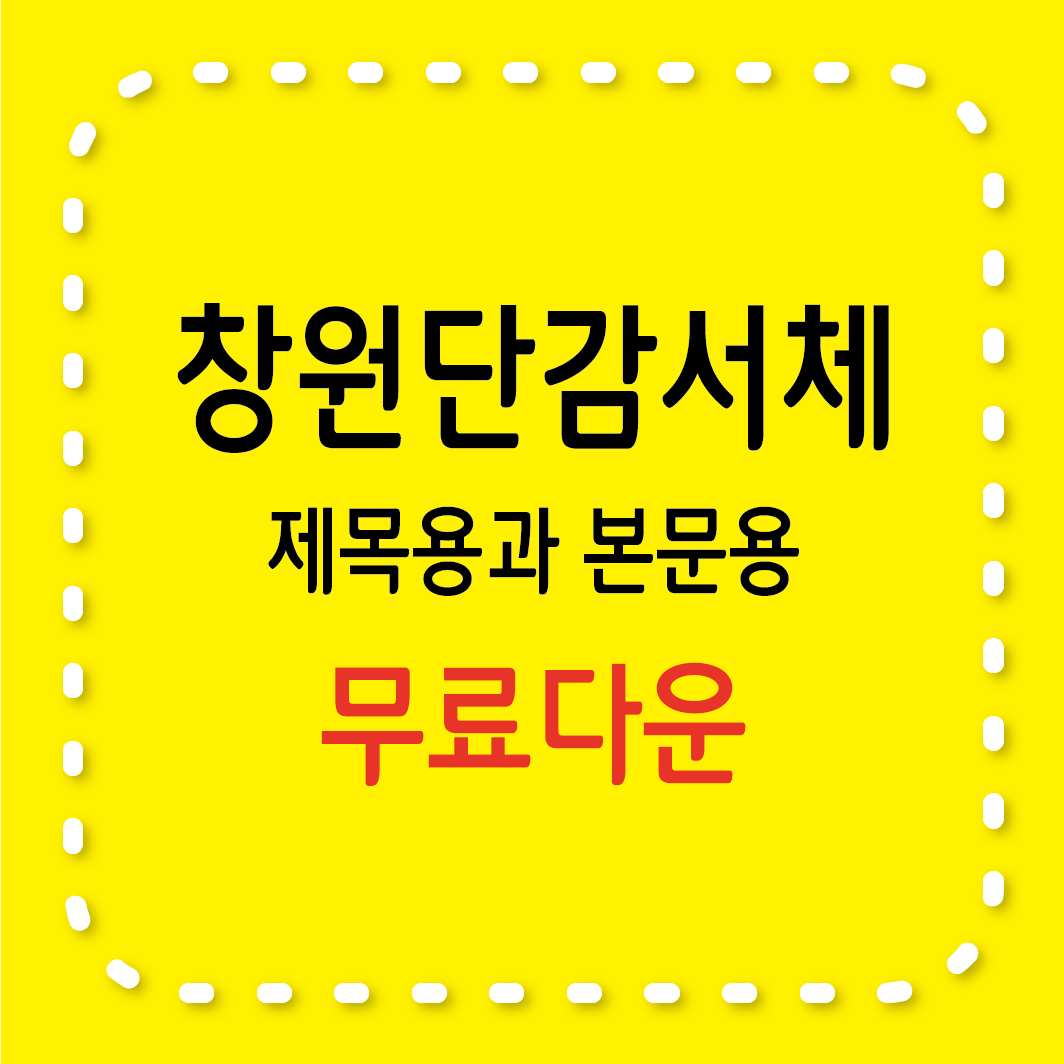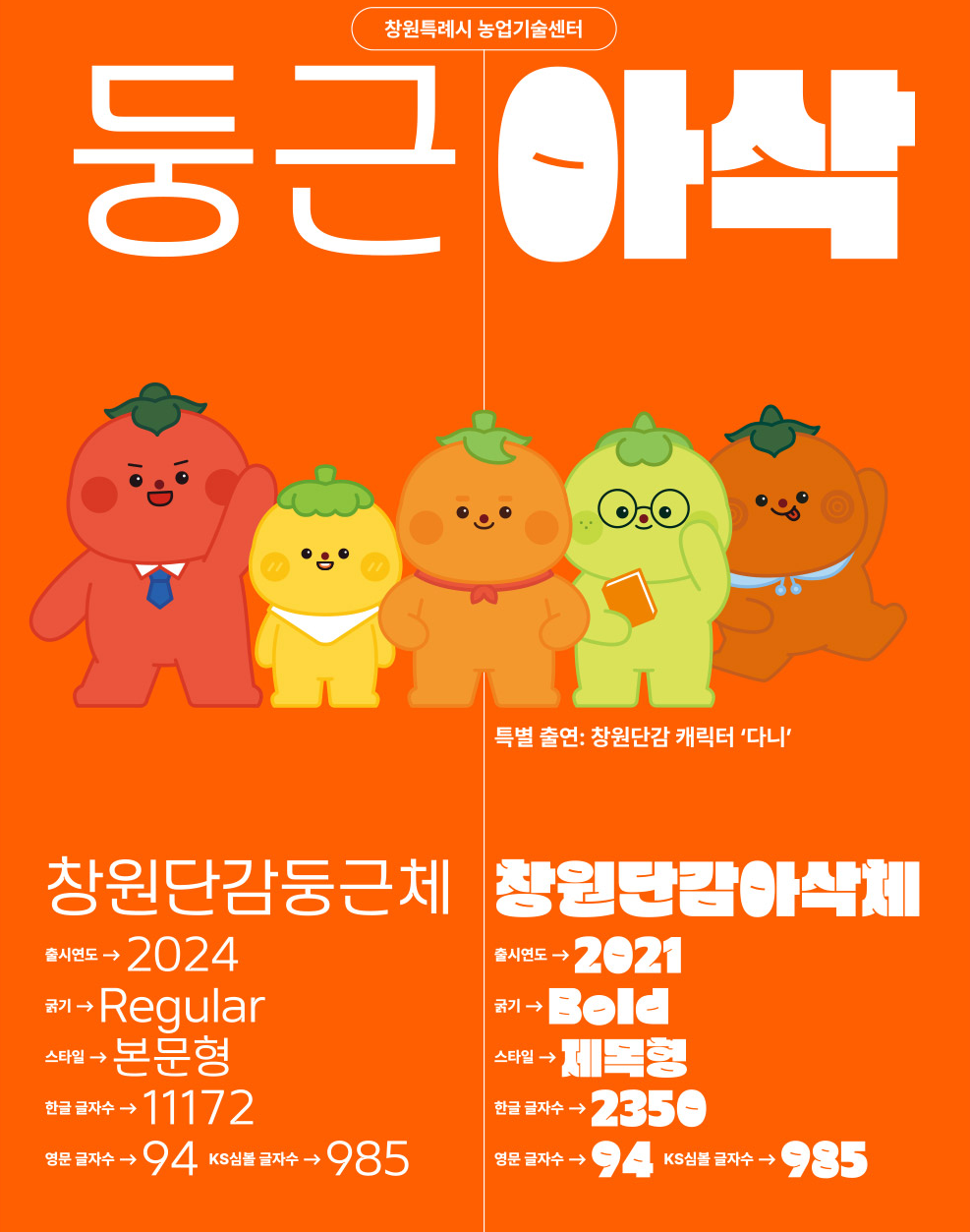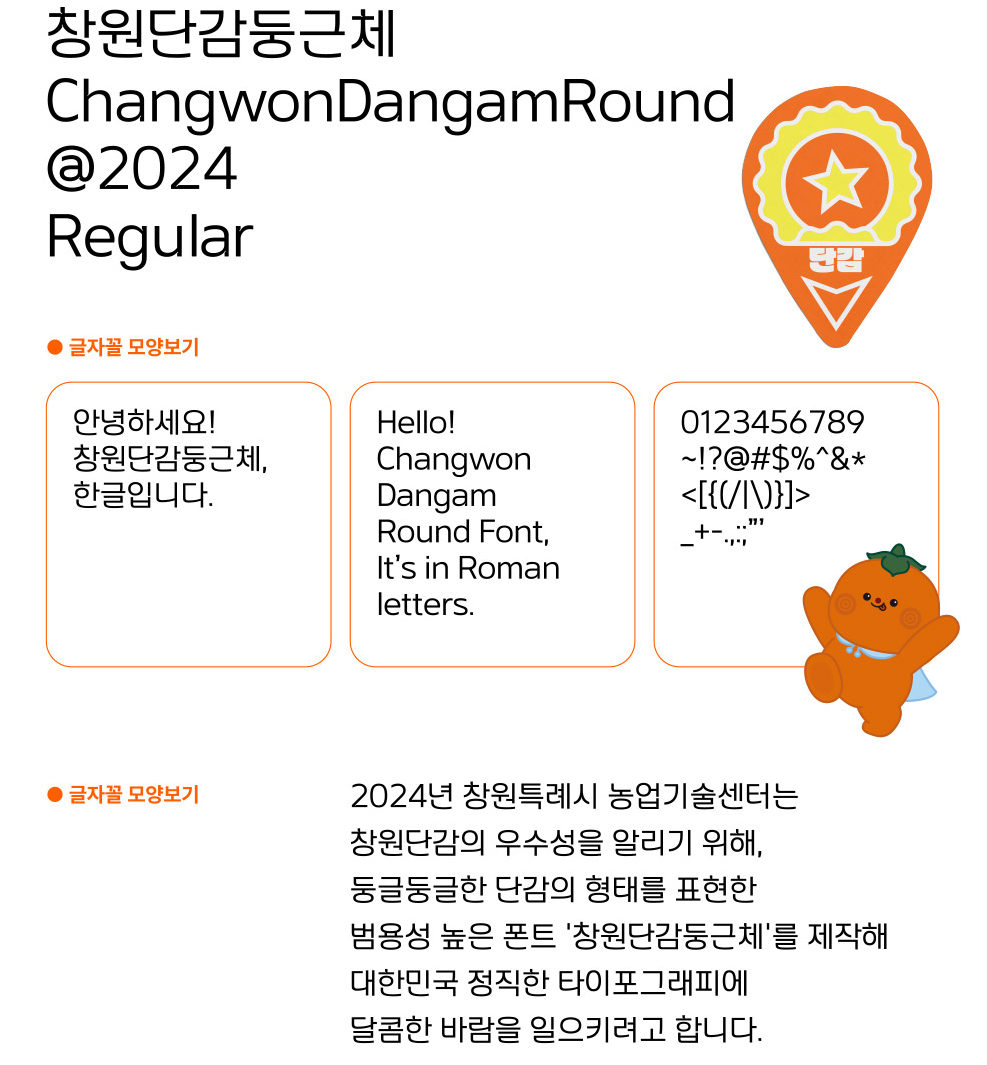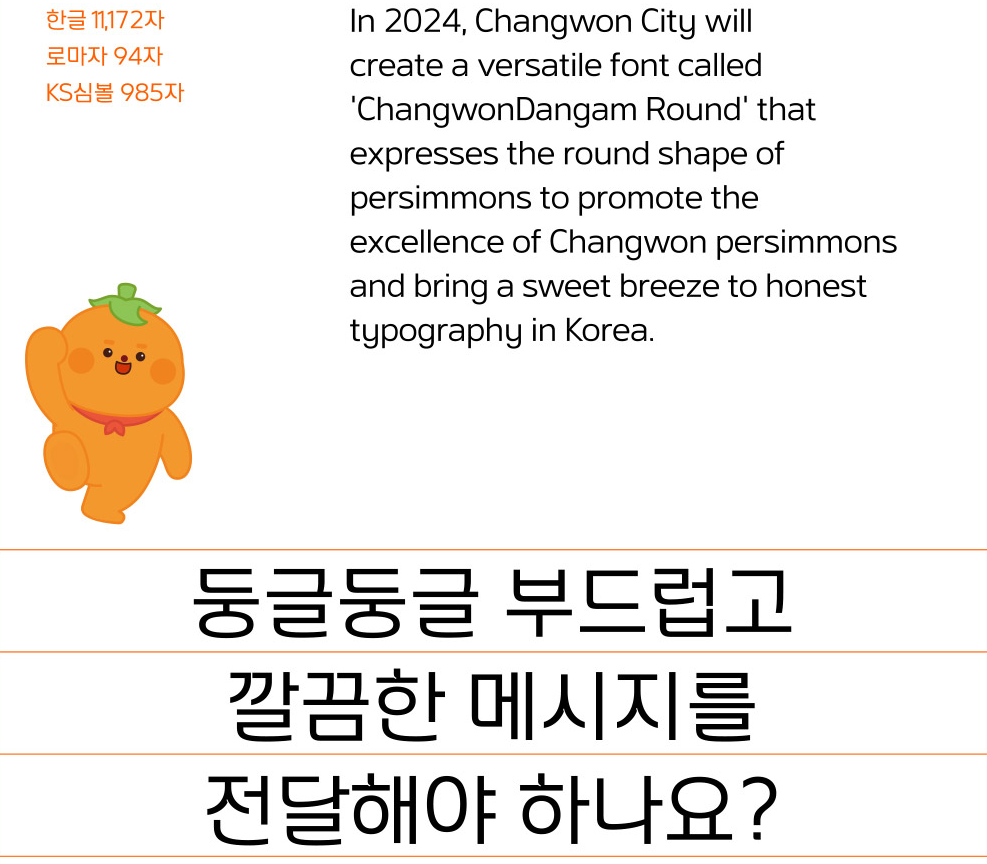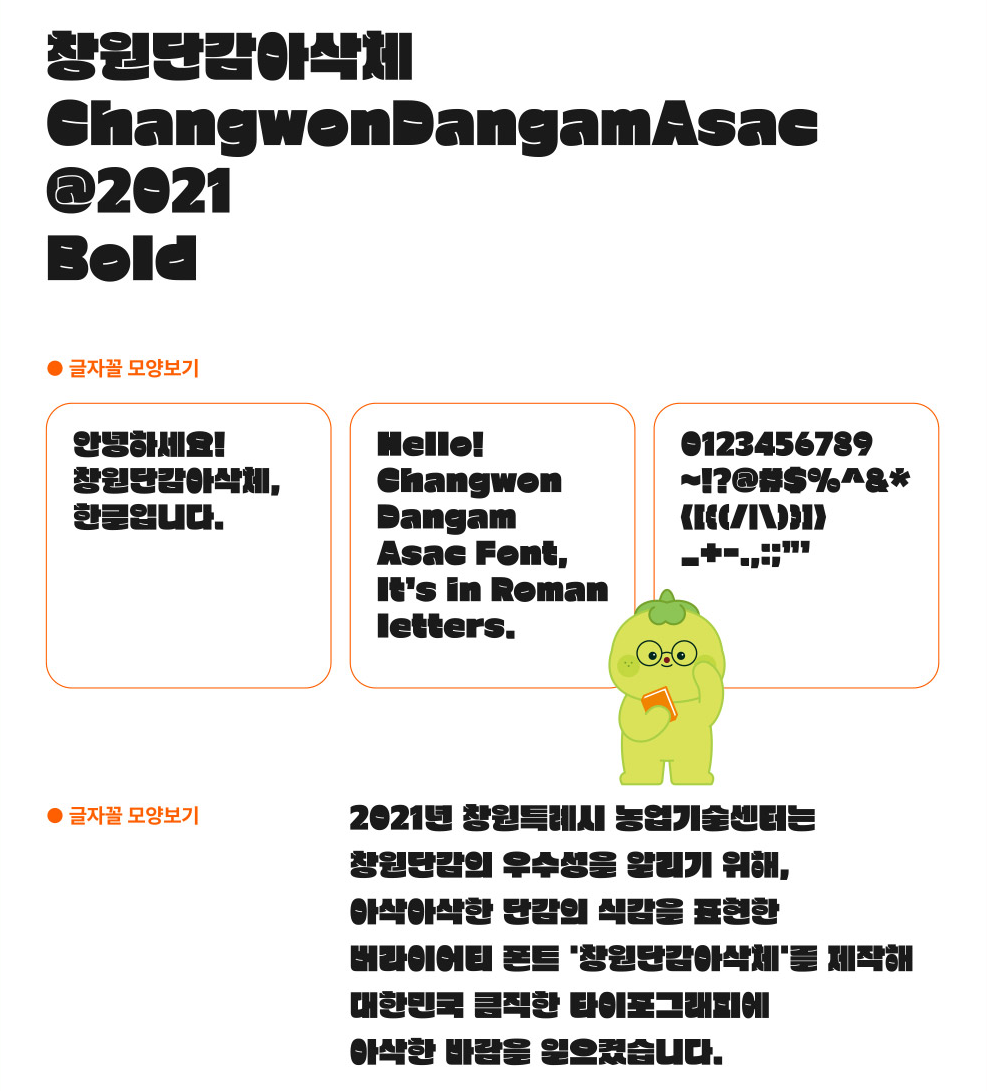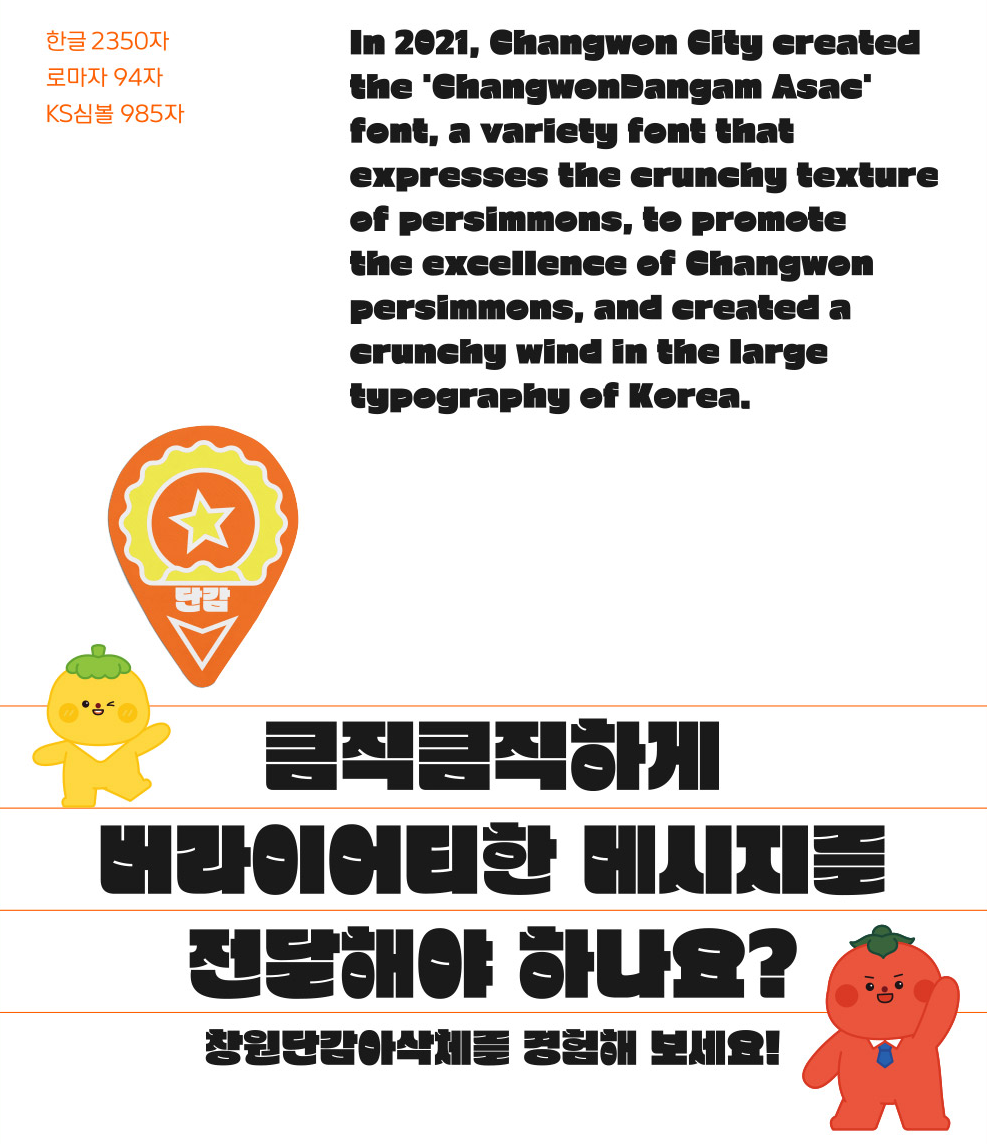
지방자치단체에서 배포하는 무료 폰트 중, 감성과 실용성을 모두 담은 서체를 찾고 계셨나요?
‘창원단감서체’는 제목용과 본문용을 모두 갖춘 감각적인 폰트로, 누구나 자유롭게 사용할 수 있습니다.
창원단감서체란?
‘창원단감서체’는 경상남도 창원시에서 공식 배포하는 무료 서체입니다.
지역 특산물인 단감을 모티브로 개발된 이 폰트는 창원시의 정체성과 따뜻한 이미지를 담아내며, **누구나 자유롭게 사용할 수 있는 오픈 라이선스 폰트**입니다.
서체 종류 및 구성
창원단감서체는 두 가지 스타일로 제공되어 용도에 따라 다양하게 활용할 수 있습니다.
- 창원단감둥근체 - 본문용, 가독성이 뛰어난 서체
- 창원단감아삭체 - 제목용, 시각적으로 임팩트 있는 디자인
활용 예시 및 특징
✔️ **공공 인쇄물, 교육자료, 웹디자인, SNS 콘텐츠 제작 등 다양한 분야에 적합**
✔️ 깔끔하면서도 친근한 인상을 주는 디자인
✔️ 로컬 브랜딩이나 지역 특산물 관련 홍보에 강력 추천
결론 요약
‘창원단감서체’는 지역의 매력을 글자에 담은 서체로, 실용성과 디자인 모두를 만족시킵니다.